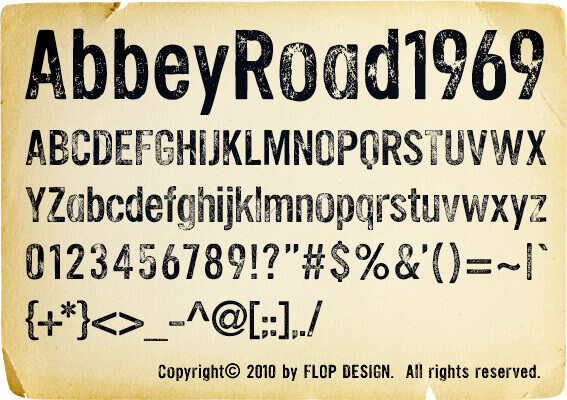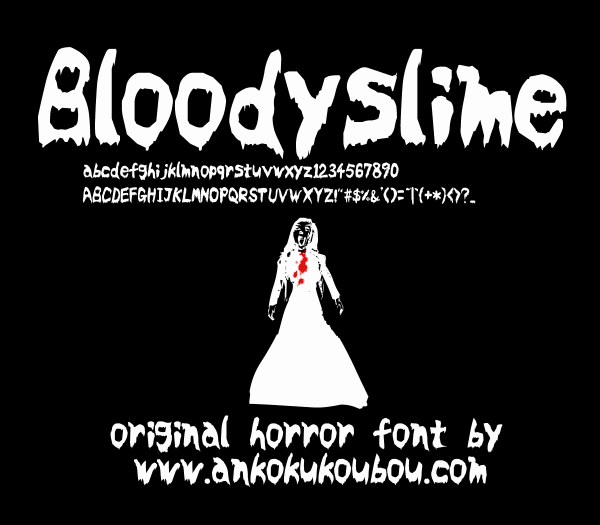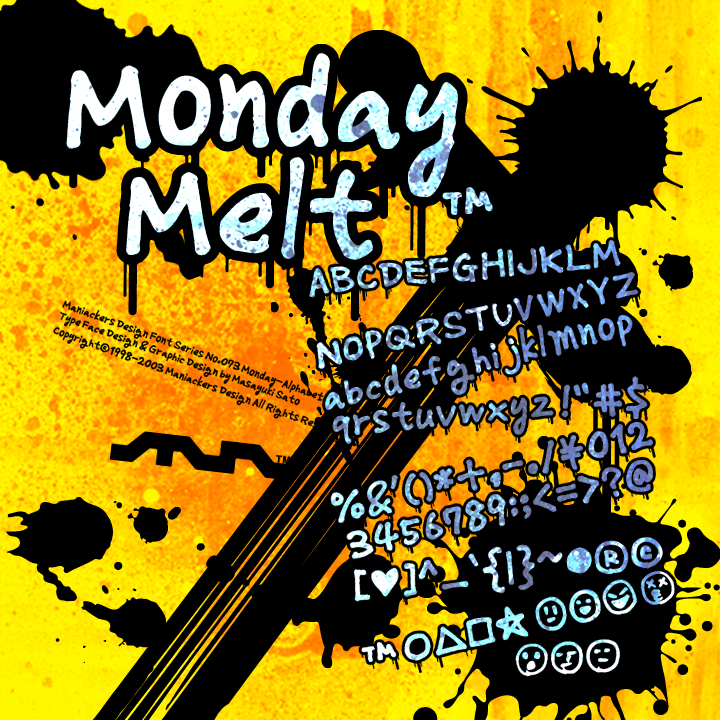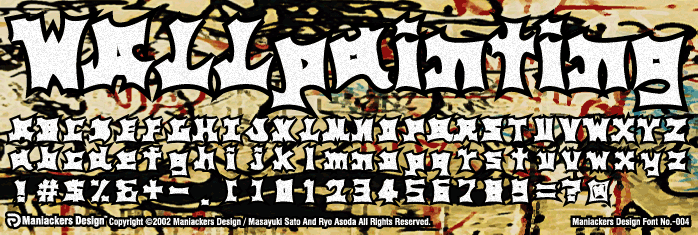
無料でダウンロードできるグラフィティフォント13点まとめ
ストリート系デザインにぴったりなグラフィティフォントを13個まとめました。グラフィティフォントとは、スプレーやフェルトペンなどを使い、壁などに描かれた落書きのことを言います。ストリート感を出したいデザインを作る際にぜひ使ってみましょう。
a dripping marker font
血が流れているような恐怖系フォント。
Another call
ハロウィンで使えそうなカッコイイホラー系英字フォント。
Bloodyslime
ポップな流血英字フォント。ポップな太目の文字で流血風のしたたりがついたデザインになっています。
Crash
とげとげっとしたデザインのフォント。はじけた感じの雰囲気を出したい時にピッタリです。
Double Feature
血が流れている太文字フォント。
Gypsy Curse font
ゾンビ映画風のフォント。
KIESIG.
もこもこ感が漂うほんわかなイメージのフォント。
Monday-AL
ノーマル(Normal)、アウトライン(Outline)、メルト(Melt)の3ファミリーが収録されている手書きフォント。
Unquiet Spirits
スプラッター映画風のフォント。
Wallpainting-AL
壁に描かれているグラフィティ・アートをイメージしたフォント。
アビーロード1969
手書きで描いたレタリングを汚して紙をクシャクシャにしたものをスキャンしたフォント。
グルーヴィーグルーヴィー
70年代をイメージしたレトロな雰囲気のフォント。
ブレイクフォント
ペンキで殴り描いたようなかっこいい系フォント。